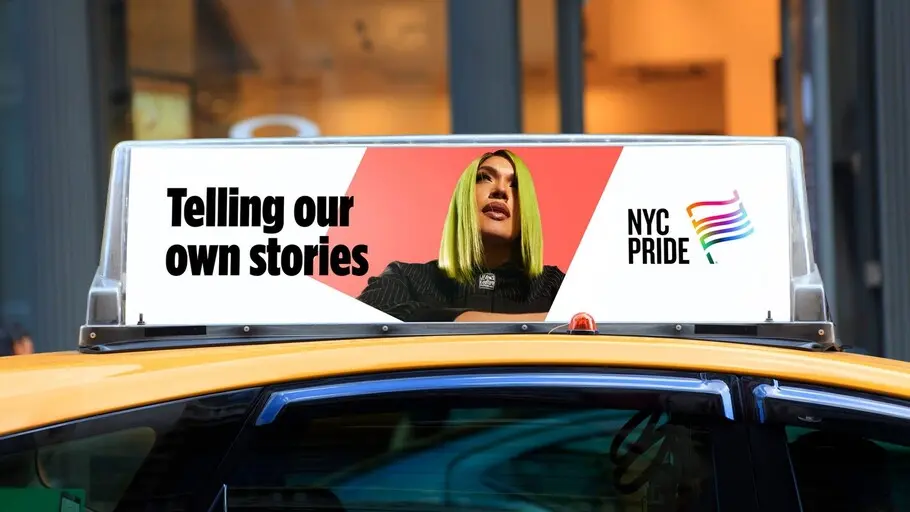
Una nueva identidad inclusiva para el Orgullo de Nueva York.
« Knockout y Gotham son recursos ideales para ayudar a transmitir la historia y la misión del Orgullo de Nueva York, que es dar voz a todas las realidades. Al mismo tiempo, reflejan que, más que una celebración anual, se trata de un compromiso con la igualdad que dura todo el año. »
Sara Soskolne, directora creativa de tipografía
Monotype y Lippincott trabajaron juntos para crear una nueva identidad sólida e inclusiva para el Orgullo de Nueva York, el evento insignia celebrado cada año por Heritage of Pride, una de las organizaciones LGBTQIA+ más significativas y con mayor trayectoria del país.
Más de 40 años después de las protestas de Stonewall en Greenwich Village, Heritage of Pride se vio de nuevo en una encrucijada. El legado del grupo, que nació tras los sucesos de Stonewall, está integrado en todo el movimiento LGTBIQA+ moderno. Como responsable de organizar el célebre desfile del Orgullo de Nueva York, The Rally y otros eventos destacados, Heritage of Pride ha sido testigo de todo: desde los primeros días de manifestaciones públicas que desafiaban el sistema orgullosamente hasta los retos, las victorias y los progresos que se han ido sucediendo.
Sin embargo, a lo largo de los años, la organización nunca se había decidido por una identidad de marca única y coherente para su evento principal, el Orgullo de Nueva York. En su lugar, siempre cambiaba los recursos visuales según el tema de cada año.
El equipo directivo de Heritage of Pride reconoció que necesitaba una identidad de marca atractiva que ayudara a la organización a promover la igualdad y a crear conciencia de sus increíbles acciones. A Lippincott le entusiasmó la idea de unirse a Heritage of Pride para ayudar a crear una nueva identidad de marca para el Orgullo de Nueva York que reflejara sus inmensas contribuciones al movimiento LGTBIQA+ y la importante labor que sigue desempeñando la organización. Monotype tuvo el honor de formar parte de este proyecto.
El objetivo de redefinir la identidad de marca era crear una sensación de inclusión y reflejar el espíritu y la importancia de la ciudad donde tiene su hogar la organización. Después de todo, estamos hablando de Nueva York, y no se debe restar importancia al significado que tienen la ciudad y sus habitantes para el movimiento LGTBIQA+. La organización acertó al elegir dos tipos de letras que guardan una estrecha relación con Nueva York para representar a la marca: Gotham® y Knockout®, ambas de los neoyorquinos Hoefler&Co®., que ahora forman parte de la biblioteca de Monotype. Seguiremos hablando de ellas un poco más adelante.
El primer paso del proyecto fue definir una nueva posición que sirviera de base para la marca y la experiencia. El nuevo propósito es servir de inspiración y apoyar a todas las personas LGTBIQA+ para que amen con orgullo y sean fieles a sí mismas. Este objetivo está estrechamente vinculado a las raíces contestatarias del Orgullo de Nueva York y a la capacidad de esta celebración anual para unificar a su comunidad y defenderla.
La nueva identidad visual gira en torno al emblema de la bandera, que es inclusivo, comunitario y muy reconocible. Se trata de una insignia con raíces históricas que captura toda la esencia del movimiento actual. La célebre bandera del Orgullo, que se ha convertido en un símbolo universal de seguridad, comunidad y alianza, es el centro de todo y refleja el espíritu de celebración y activismo de la organización. Exhibe sutilmente las letras «NYC» y cuenta con un gradiente adaptativo que aporta flexibilidad a la narrativa e incluye a los distintos subgrupos de la comunidad LGTBIQA+.
Gotham y Knockout aportan mucho más a la historia que la autenticidad urbana de Nueva York. Por su parte, Knockout hunde sus raíces en la tipografía ecléctica de las octavillas del siglo XIX. Aporta un espíritu de lucha incansable que rinde homenaje a la determinación de las iniciativas de Heritage of Pride, que llevan décadas abogando por la igualdad y la representación.
Esa determinación que inspira Knockout se equilibra a la perfección con la apertura y la cercanía de Gotham, una visión moderna del estilo que se emplea en la señalización de las calles de la ciudad. Las formas elementales de esta fuente están diseñadas para expresar tantas voces diferentes como sea posible. El uso clave de Gotham Condensed Extra Black permite a la organización hablar con una voz firme, pero amable, asertiva, pero inclusiva. Heritage of Pride se une a una larga lista de usos destacados de Gotham, entre los que se incluye la campaña de Obama.
«Es un honor que una causa y una organización tan importantes hagan uso de nuestros tipos de letras», afirma Sara Soskolne, directora creativa de tipografía de Monotype. «Knockout y Gotham son recursos ideales para ayudar a transmitir la historia y la misión del Orgullo de Nueva York, que es dar voz a todas las realidades. Al mismo tiempo, reflejan que, más que una celebración anual, se trata de un compromiso con la igualdad que dura todo el año».
Jenifer Lehker, socia de diseño de Lippincott, añade: «El Orgullo de Nueva York se reconoce en todo el mundo no solo como un modelo de seguridad, comunidad y alianza, sino también como símbolo de protesta y activismo. Monotype captó la idea y ha contribuido de forma excepcional a nuestra causa con las familias de fuentes Gotham y Knockout, que reflejan muy bien el espíritu y el legado de la marca».
La lucha por la igualdad no termina nunca, y Heritage of Pride lo sabe bien. Esperamos que esta nueva identidad del Orgullo de Nueva York ayude a la organización a avanzar hacia una nueva era de lucha y activismo, y es un honor haber aportado, al menos, un granito de arena.